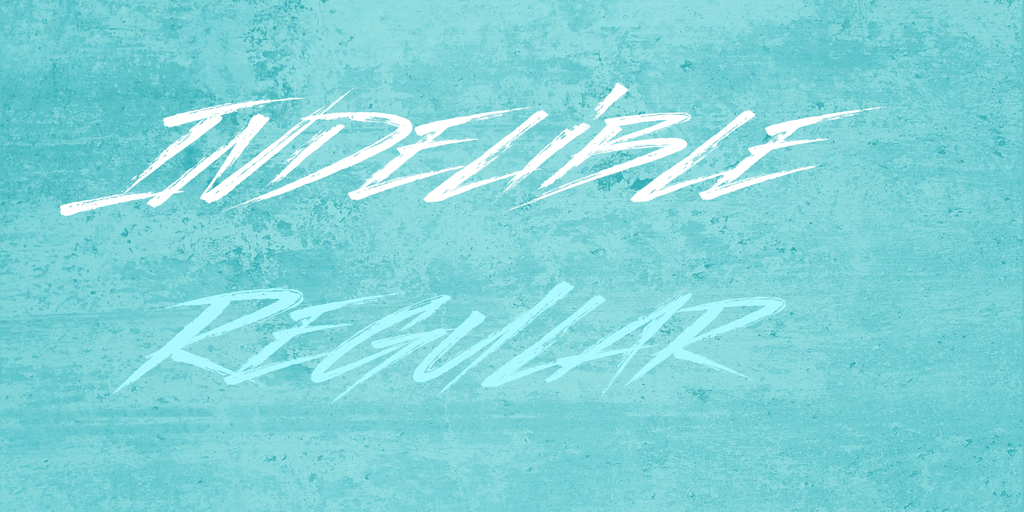
A fonte ‘Indelible’ oferece um toque elegante e criativo ideal para designers buscando uma mistura suave entre escrita a mão e tipografia digital, perfeita para qualquer projeto pessoal ou de pequeno porte. Desenvolvida pelo designer Hamilton, essa brush font tem um estilo único que combina detalhes delicados com linhas fortes e fluidas, o que torna ela uma escolha ótima para criações em design gráfico, moda ou arte digital. Com sua disposição agradável e versatilidade, ‘Indelible’ permite aos designers experimentar diferentes estilos de escrita manual sem comprometer suas necessidades comerciais. Completamente livre para uso pessoal, o designer Hamilton oferece suporte através do email  se você planeja aplicá-la em um projeto comercial. Seja você uma novato ou um profissional experiente, a ‘Indelible’ é uma fonte que traz vida e personalidade a qualquer trabalho de design que você realizar.